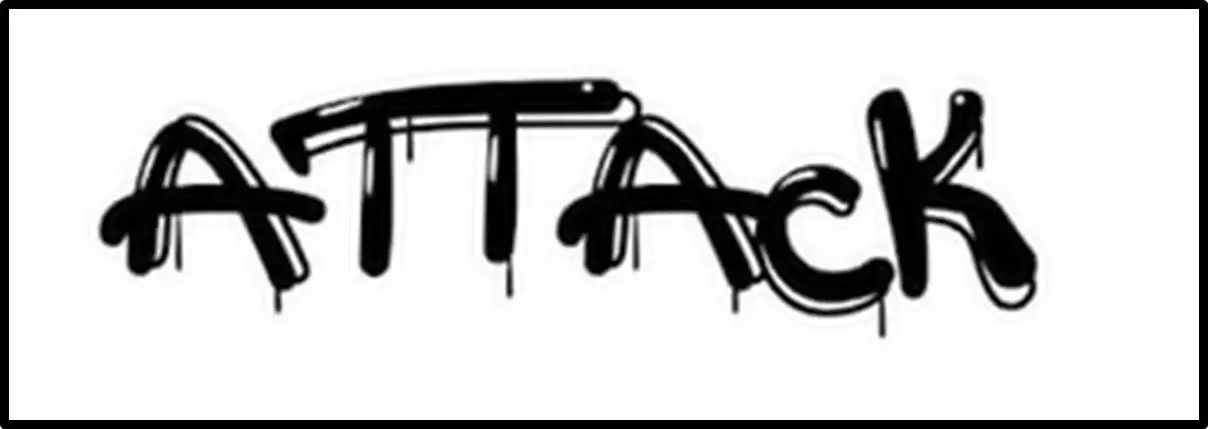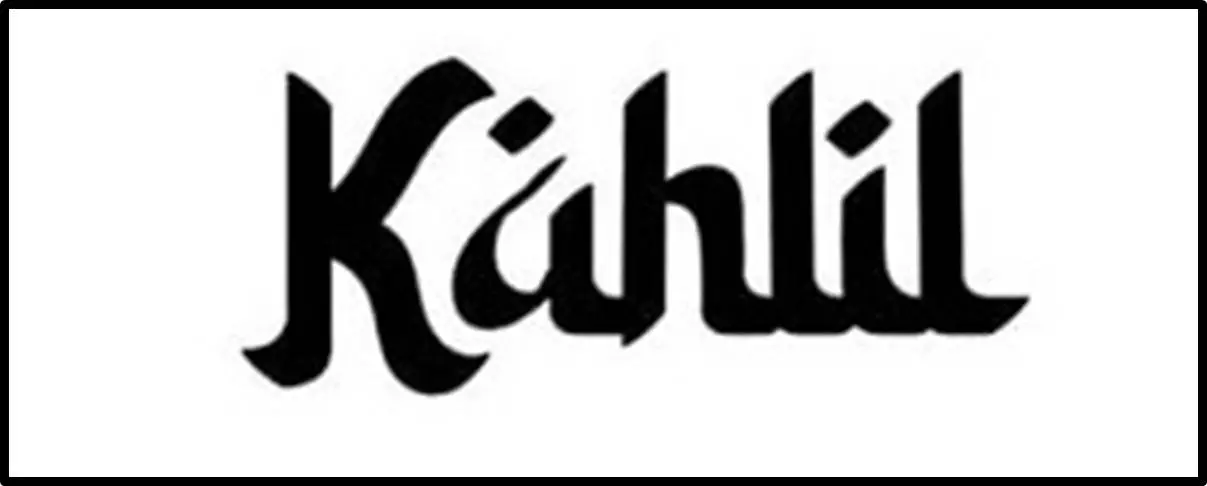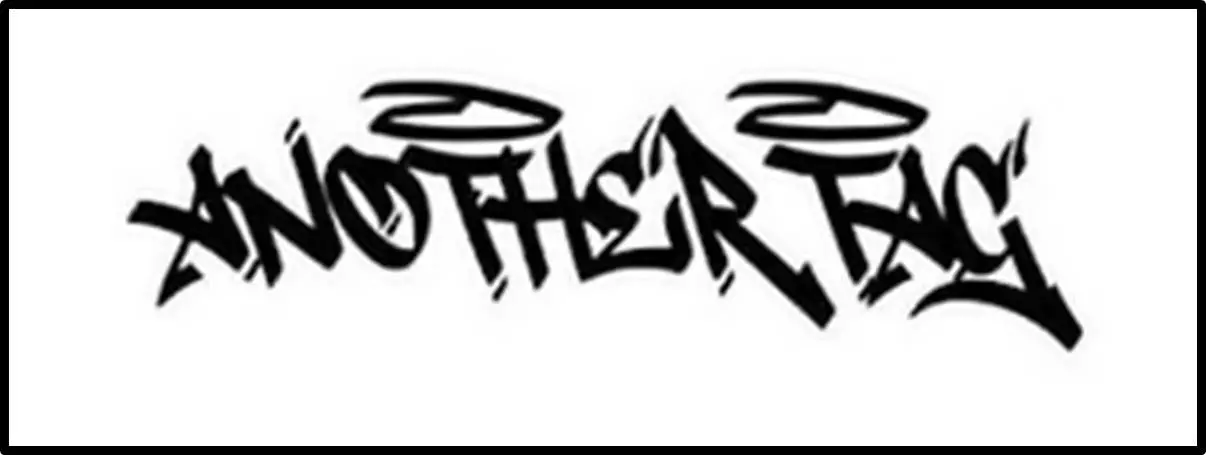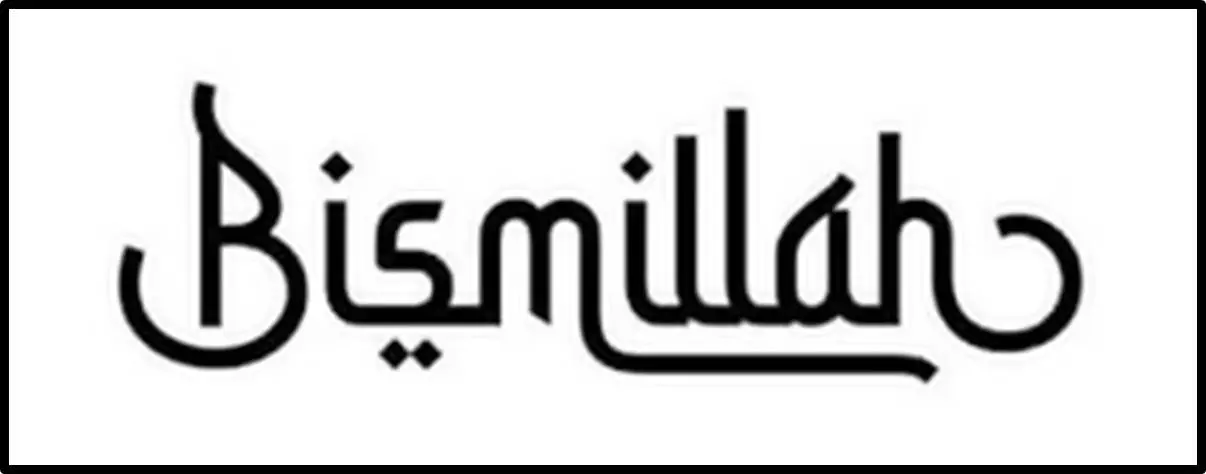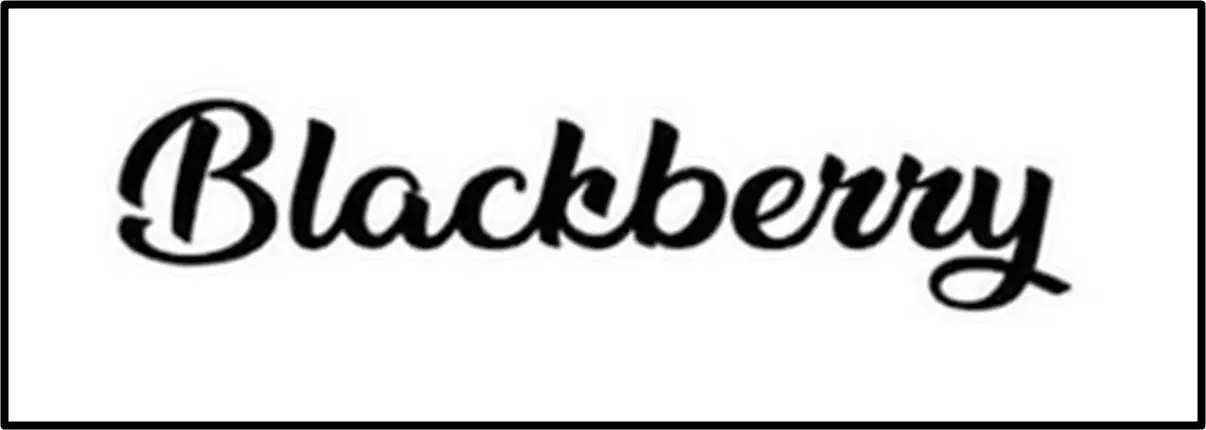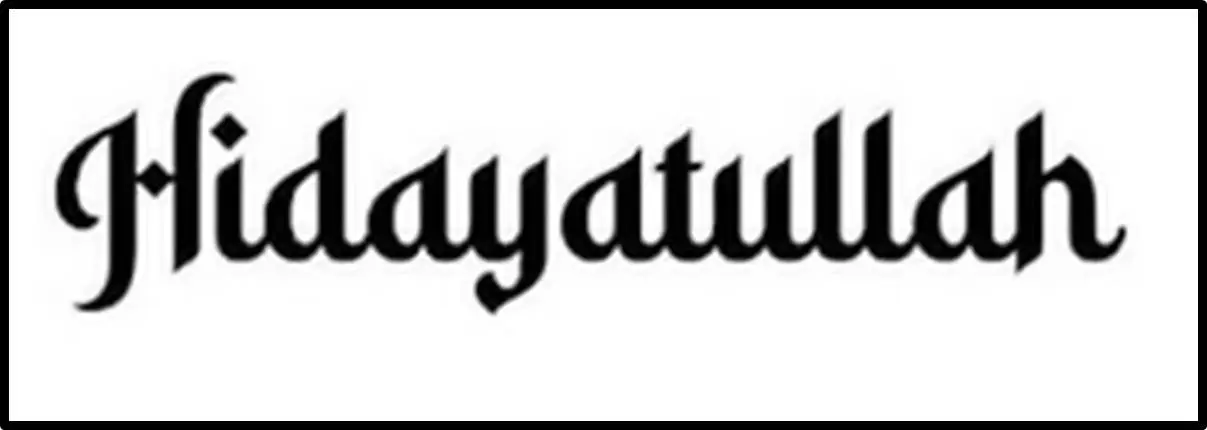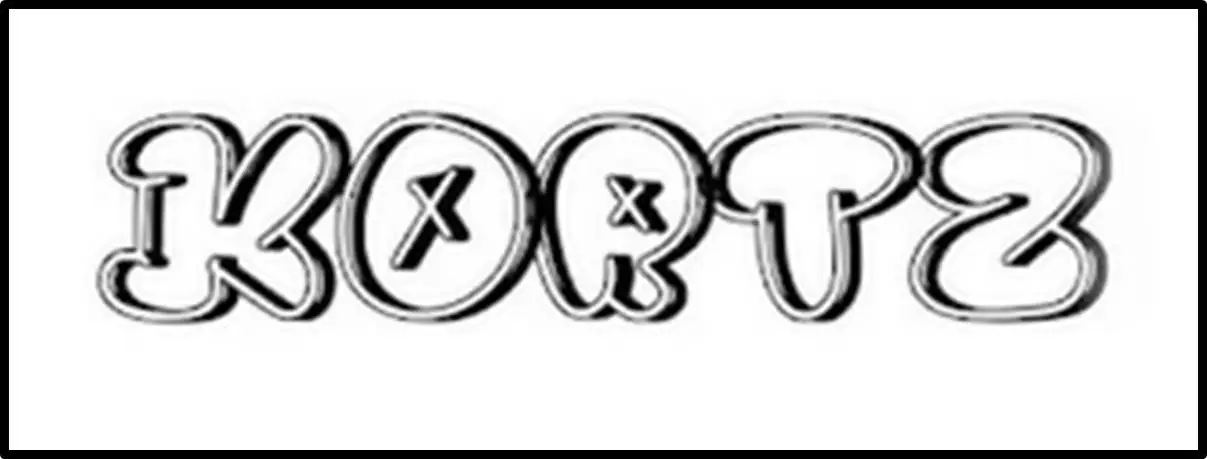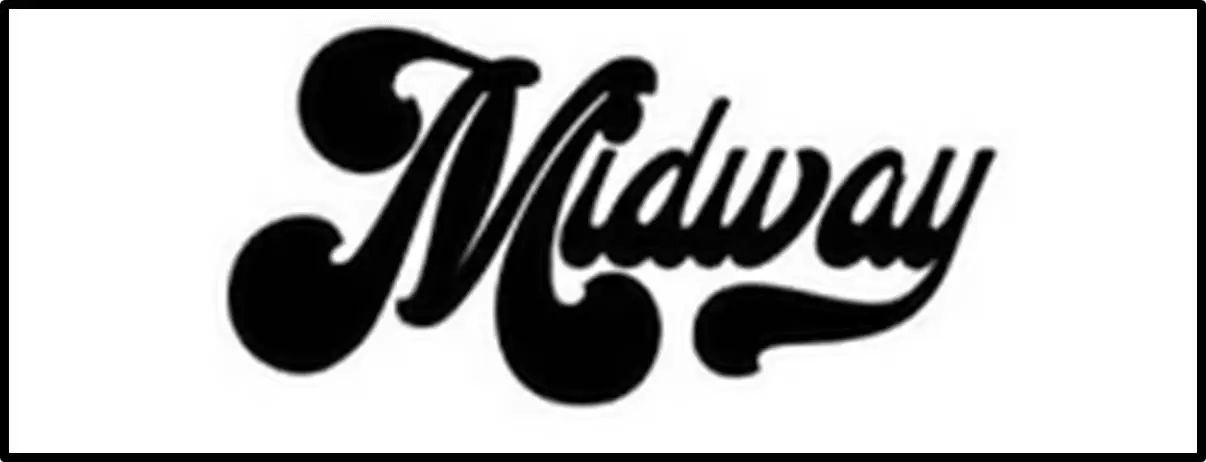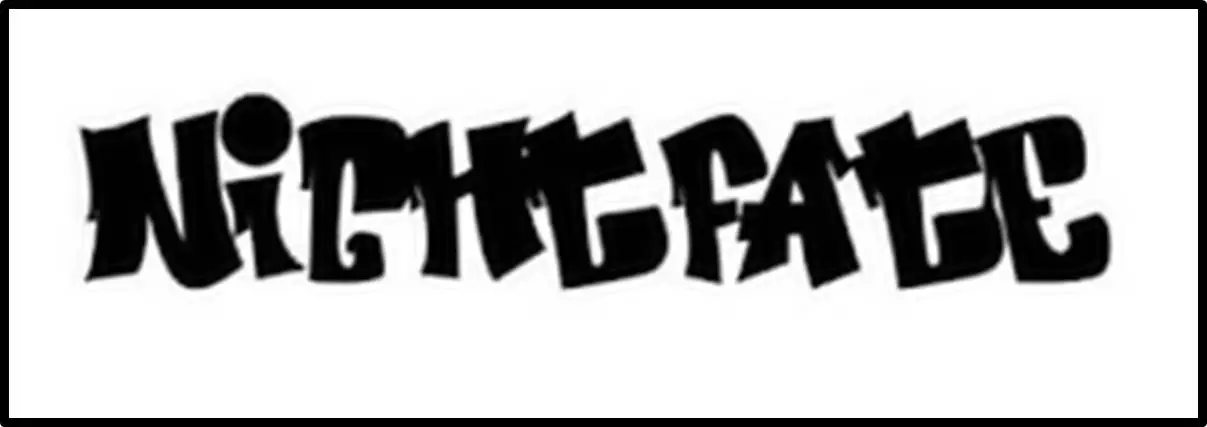
Download Font PixelLab Keren Terbaru (Arabic, Grafity, Logo, Api, Racing)
Download Font PixelLab Keren – Jaman dulu saat anda membuat design atau mengubah photo memakai netbook atau computer dan harus juga kuasai aplikasi buat mengubah atau membuat design itu karena tehnologi memanglah belum berkembang.
Tetapi, saat ini anda dapat secara mudah lakukan koreksi photo, membuat design atau membuat e-book dengan tulisan kece dengan mudah.
Download Font PixelLab Keren Terbaru (Arabic, Grafity, Logo, Api, Racing)
Saat ini anda bisa juga percantik design anda dengan font PixelLab kece yang dapat anda peroleh dari internet secara gratis. Kabar baiknya kembali, buat lakukan hal itu anda tak perlu memakai netbook atau computer, kamu dapat unduh font PixelLab lewat ponsel.
Mengenai Aplikasi PixelLab
PixelLab sebagai aplikasi ubah photo yang dapat dipakai di piranti Andorid, iPhone dan PC (memakai emulator). Dengan aplikasi PixelLab kita dapat membuat beragam jenis koreksi design grafis dan photo.
Umumnya beberapa orang memakai aplikasi ini buat membuat poster, gambar cuplikan atau quote, design grafis, meme gambar, stiker, gambar wujud 3D dan ada banyak lagi.
Aplikasi ini benar-benar enteng, penampilan yang nyaman, banyak memiliki feature desan dan gampang dipakai buat pemula sekalinya. Banyak tersedia opsi text, text 3D, dampak text, stiker, warna dan bermacam font keren.
Mengenai Font PixelLab
Font PixelLab secara umum sama juga memakai font yang umum dipakai pada aplikasi editing dan aplikasi pengolah data. Aplikasi tipe ini dapat menambah beragam jenis tipe font, termasuk PixelLab.
Unduh Font PixelLab Keren
Banyak mentahan font PixelLab yang dapat anda unduh gratis di internet, tetapi tidak mudah buat menemukan font PixelLab yang pas buat desain. Maka dari itu, artikel dibikin buat mengumpulkan font kece buat membuat Logo, Q yang lain dan uotes.
Berikut ialah beberapa referensi font PixelLab kece yang dapat anda pakai buat percantik photo atau desain gambar.
1. Blazed
Blazed
Font PixelLab racing sebagai referensi pertama ialah blazed. Font yang ini pas dipakai sebagai logo nomor motor balap. Nach, untuk anda yang hoby dengan motor balap karena itu anda langsung bisa saja memakai font PixelLab ini. Sama dengan namanya, huruf dan angka yang ada di font ini mempunyai design yang terlihat seperti api yang berkobar.
2. Faster One
Blazed
Font PixelLab seterusnya yang paling direkomendasikan ialah font faster one. Font yang ini masih pas dipakai oleh beberapa pencinta balap yang ingin membuat design yang berkaitan erat dengan dunia racing balap. Font ini diasumsikan dengan dunia balap karena ada efek horizontal yang ada pas di samping segi kiri huruf.
3. Beautiful People
Beautiful People
Referensi font PixelLab selanjutnya ialah Beautiful People, font PixelLab buat quotes. Ini karena font ini mempunyai angka yang elok yang seperti terlihat huruf tegak berlanjut dengan sentuhan modern. Jika anda hoby membuat quote yang memberikan inspirasi buat diupload ke sosial media karena itu anda dapat memakai font yang satu ini.
4. Bloodseeker
Bloodseeker
Font PixelLab kece seterusnya yang jangan anda terlewat ialah bloodseeker. Dengan font ini anda dapat membuat tulisan atau logo yang bertopik gothic dan dapat memberi dampak horor untuk logo anda atau tulisan. Penampilan font bloodseeker ini kelihatan bak tulisan yang dicatat langsung dengan luas hingga kelihatan garis serat yang terlihat seperti goresan kuas.
5. Cassandra
Cassandra
Untuk anda yang menyenangi font cantik, karena itu anda dapat mencoba memakai font PixelLab aesthetic Cassandra. Font yang ini sebagai huruf tegak berlanjut yang demikian gampang dibaca. Font yang ini pas sekali anda pakai buat membuat undangan pernikahan karena mempunyai design yang sederhana tetapi kelihatan menawan.
Selain 5 font PixelLab di atas, aku akan memberi font kece berdasar kelompok design, salah satunya Logo, Quotes, Racing, Grafiti, Arab, Api, Tulisan Tangan dan 1 pack font yang sejumlah ribuan. Baca secara lengkap di bawah ini.
Demikian beberapa referensi font PixelLab kece yang dapat anda pilih. Janganlah lupa pilih font yang sesuai watak dan opsi design anda karena tiap font mempunyai kekhasan dan kelebihan masing-masing.